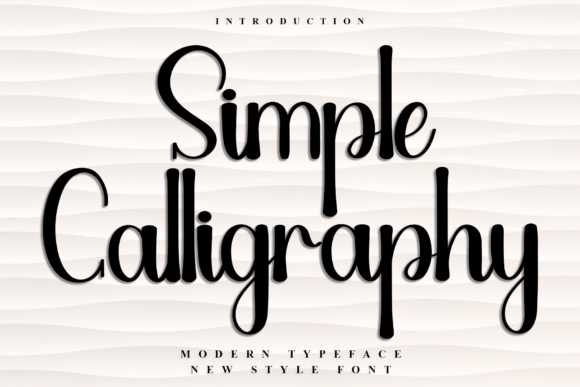
Simple Calligraphy
Encontrar los elementos de diseño adecuados puede ser un desafío, pero Simple Calligraphy ofrece una colección excepcional que eleva tu trabajo al instante.
Elaborado con precisión, Simple Calligraphy proporciona vectores limpios, tipografía suave y una licencia comercial para tu tranquilidad.
Ya sea que estés creando productos POD (impresión bajo demanda), invitaciones de boda o gráficos para redes sociales, Simple Calligraphy es una opción ideal.